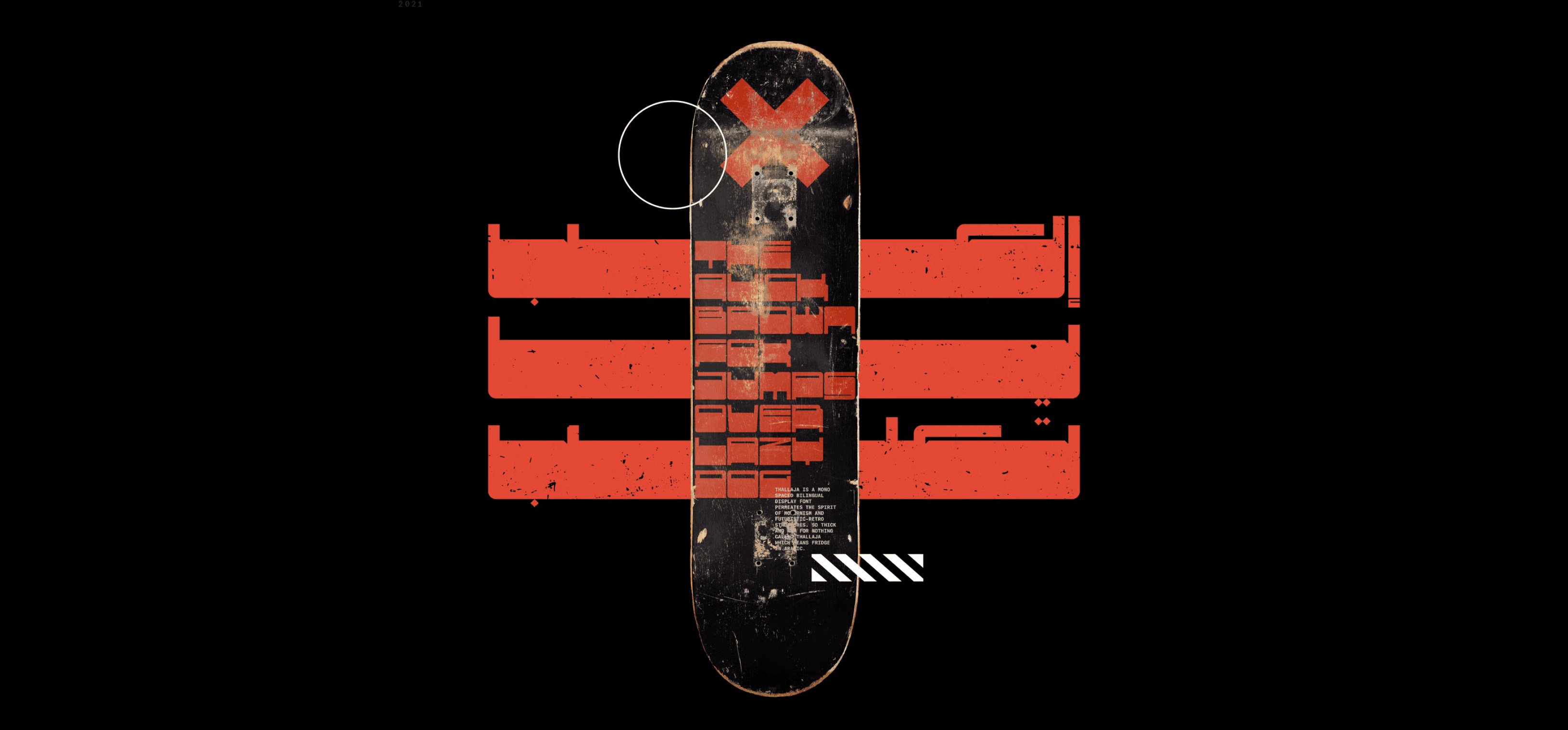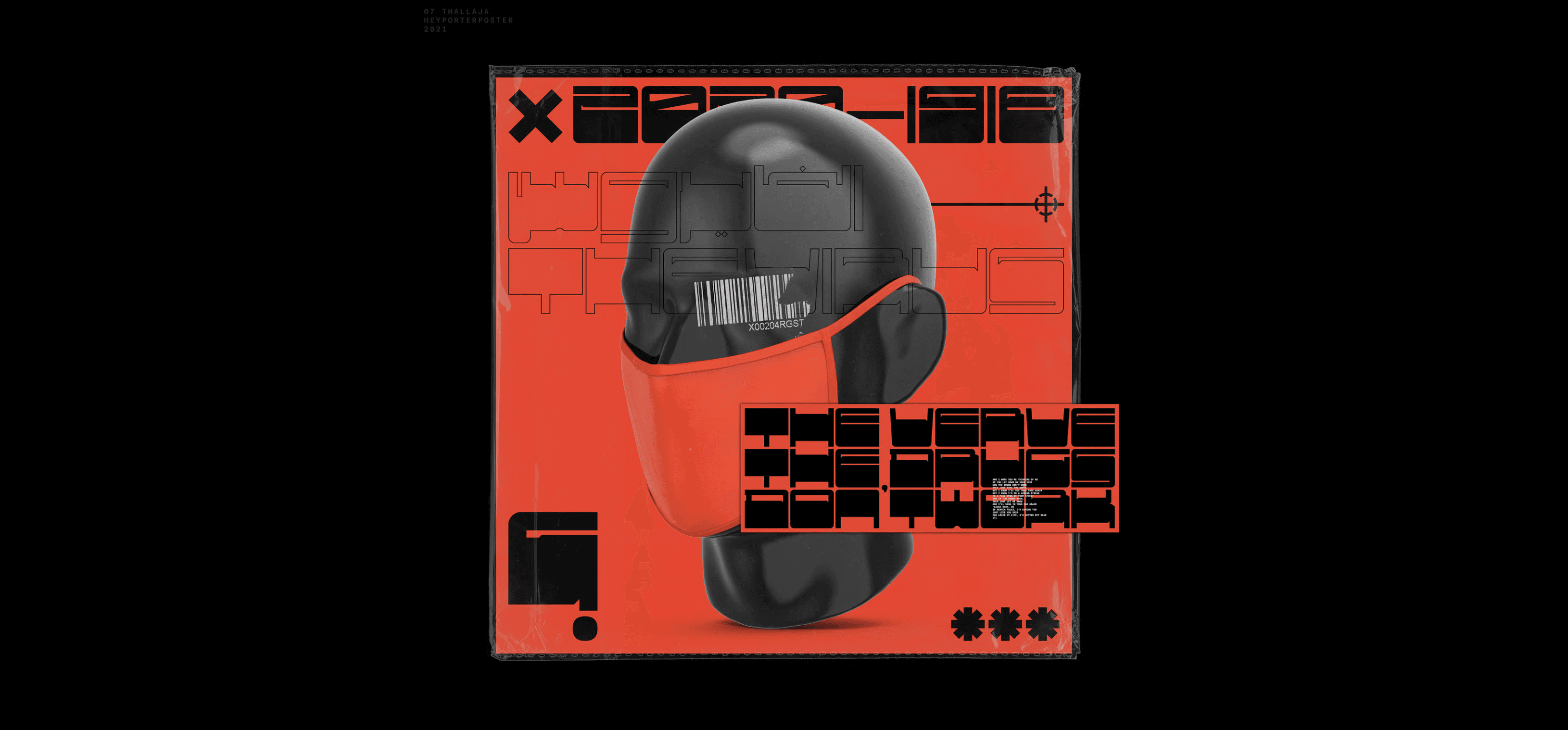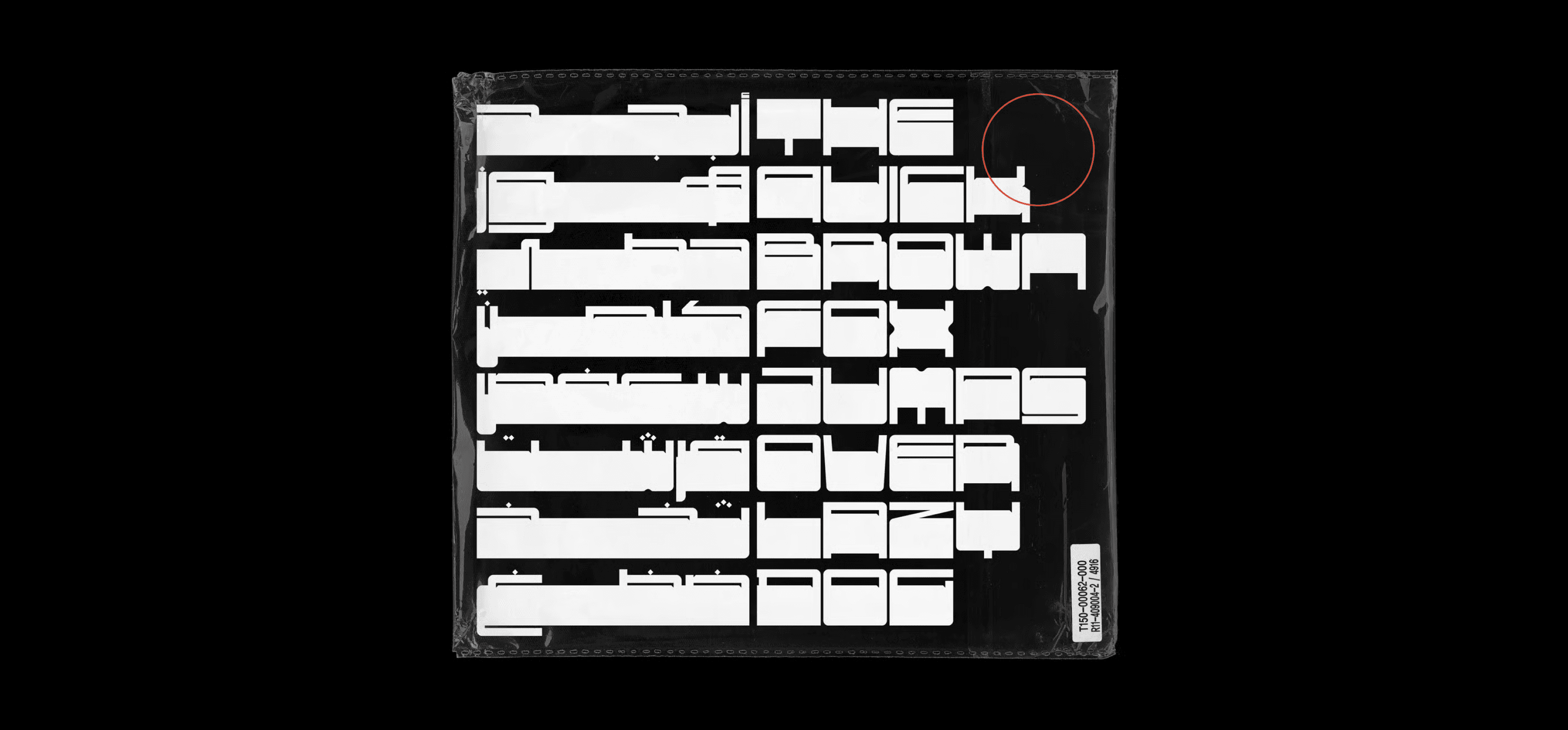
هو خط عرض أحادي المسافة ثنائي اللغة، مشبع بروح الحداثة والهياكل الرجعية المستقبلية. سميك للغاية، وليس عبثًا أنه يُدعى 'ثلاجة'، وهو ما يعني بالإنجليزية Refrigerator.